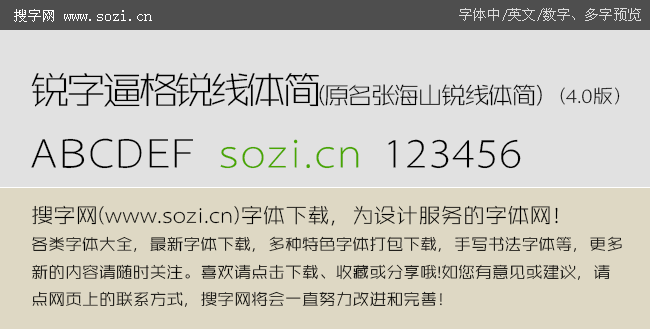
銳字逼格銳線體簡4.0(原張海山銳線體簡)
搜字網(wǎng)提供一款銳字逼格銳線體簡4.0(原張海山銳線體簡)中文字體下載,銳字逼格銳線體簡是一款以線體為原形設(shè)計的中文藝術(shù)字體,字體簡潔漂亮,效果非常出色,GBK編碼收字更全,適合應(yīng)用于廣告設(shè)計、名片設(shè)計、包裝印刷、產(chǎn)品設(shè)計等應(yīng)用。